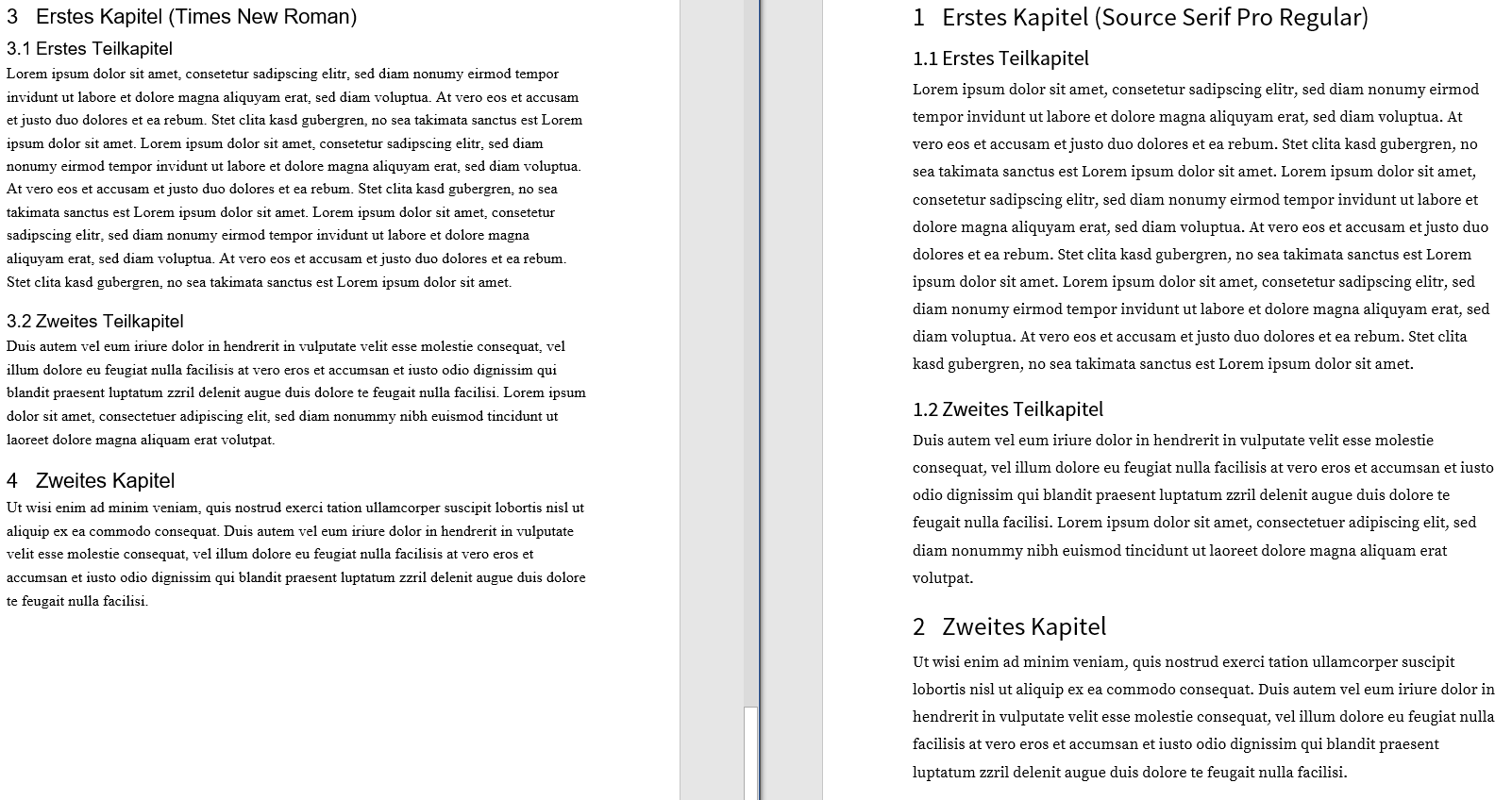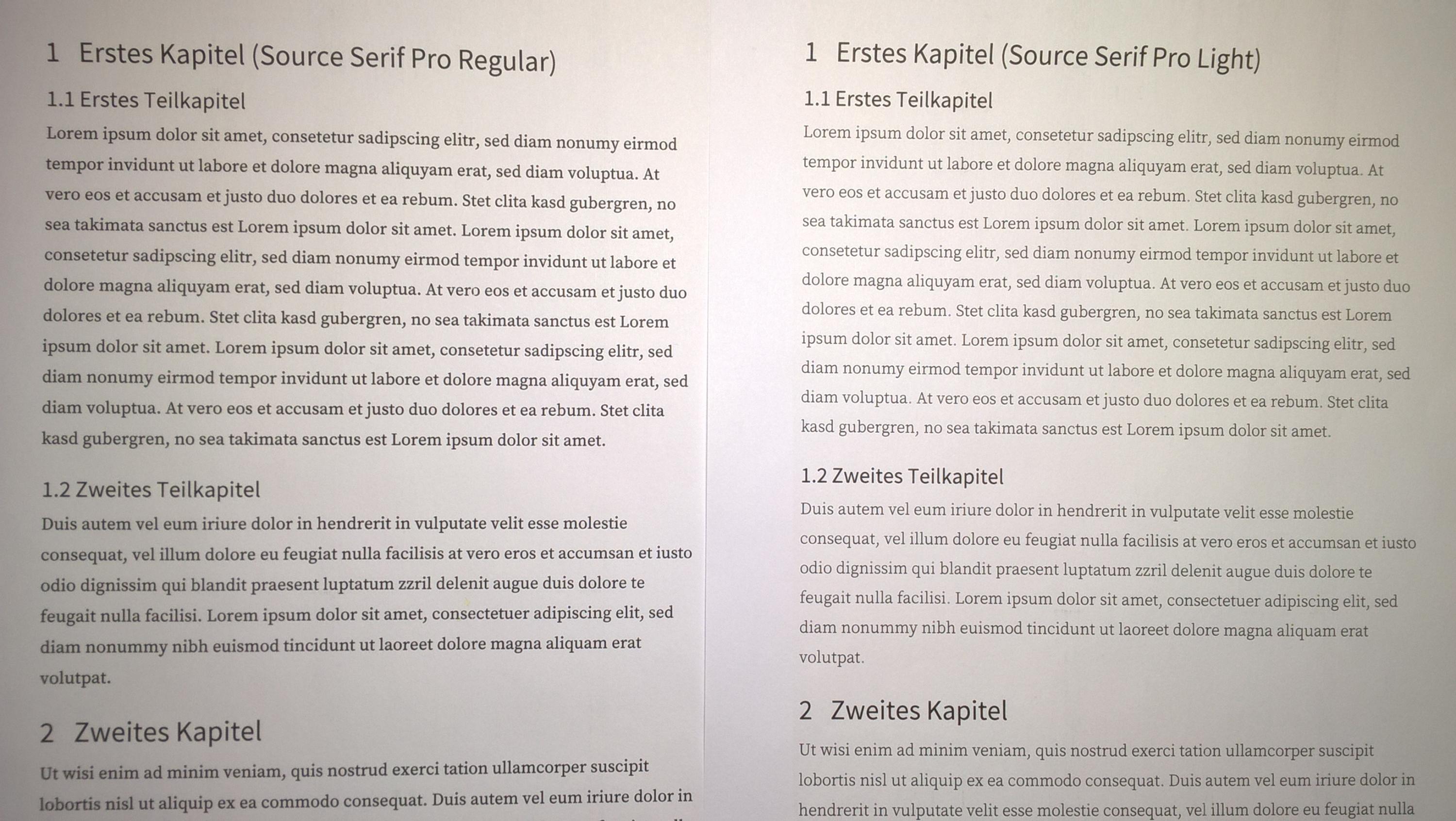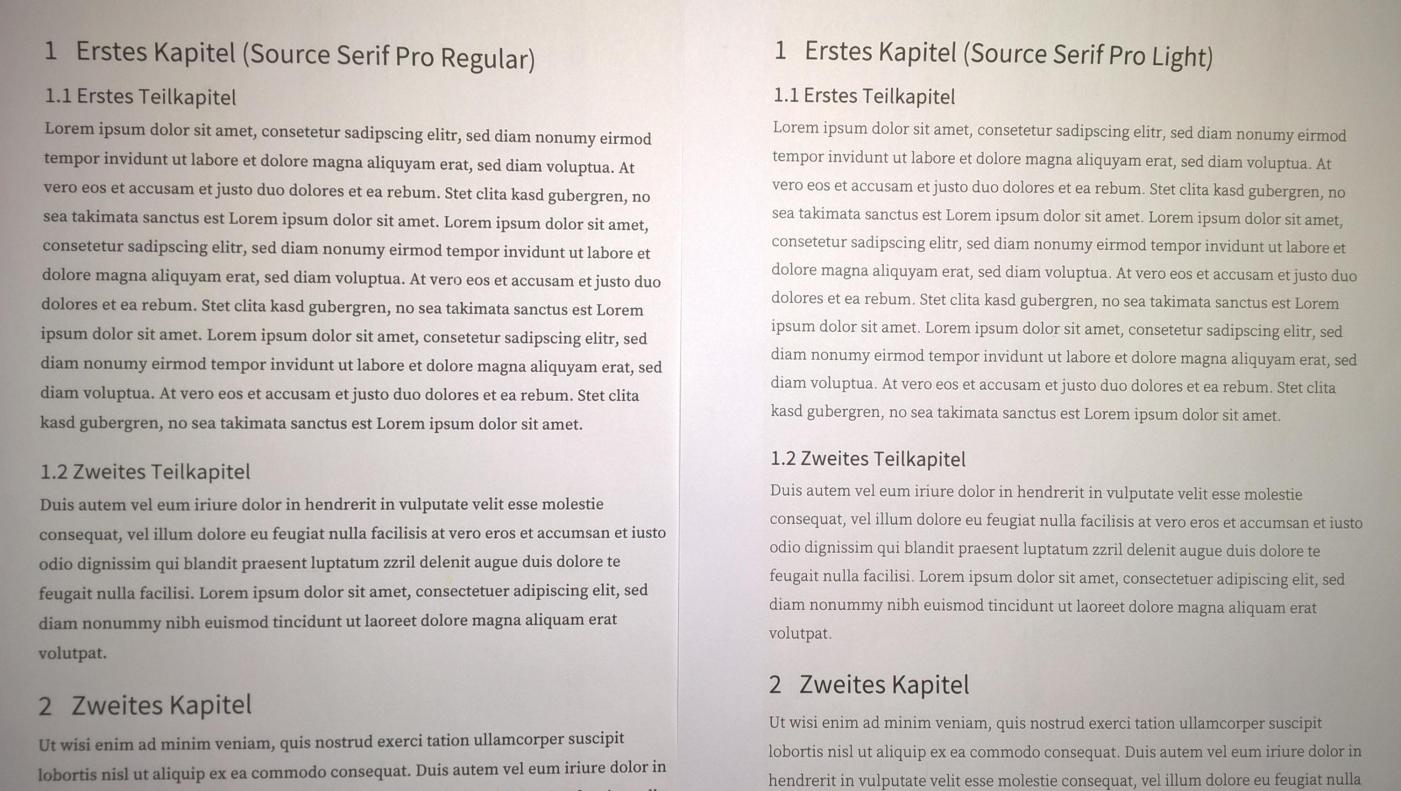
Suche Schriftart für einen Projektbericht
ich muss in der ersten Phase meiner Bachelorarbeit einen Projektbericht anfertigen und suche dafür passende Schriften. Mir persönlich ist die Verwendung von Ligaturen wichtig, da ich finde, dass sie das Schriftbild verbessern.
Ich habe mir bereits einige Schriften von verschiedenen Seiten angeschaut, bin aber nun bei Adobes Source Sans Pro und Source Serif Pro hängengeblieben.
Für Überschriften verwende ich Source Sans Pro mit den von Word (2016) verwendeten Schriftgröße. Der Fließtext hat eine Schriftgröße von 12 pt und nutzt die Schriftart Source Sans Seri Pro Light. (Die Regular-Variante empfand ich zu dick.)
Dazu würde ich gerne eure Meinung hören. Findet ihr das ansprechend, oder habt ihr Tipps oder gar andere Schriftartenvorschläge, die eventuell besser geeignet wären?
PS: Interessanterweise scheint Word 2016 beim Erstellen der PDF-Dateien in Bilder zu konvertieren. In keinem PDF-Programm kann ich den Text markieren. :-?
Das sind gute Schriften, ich denke damit bist du auf der sicheren Seite.
Bei mir am Laserdrucker wirkt der Fließtext aber zu leicht. Finde ihn nicht gut lesbar. Wie wird das später gedruckt? Ein Tintenstrahldrucker dickt den Text noch an, dann ist es vielleicht ok.
danke für deine Antwort. Okay, ich teste es mal hier am Laserdrucker. Ich schreibe das Dokument zurzeit an einem 13"-Notebook, sodass das Schriftbild möglicherweise einfach verfälscht wirkt.
Den Projektbericht werde ich im Copyshop drucken lassen. Die werden vermutlich gute Laserdrucker nutzen.
Schau dir mal auf Druckerchannel die Testberichte an. Es ist keineswegs so, dass das Schriftbild bei teuren und im Ranking höher positionierten Laserdruckern besser ist. Für einen Copyshop dürften Langlebigkeit, Geschwindigkeit, Tonerkosten u. s. w. wichtiger als das Schriftbild sein.
Das wäre sehr ärgerlich. Na gut, dann eventuell doch lieber zuhause drucken? Oder gibt es da bessere Optionen?
Zum Thema: ich habe noch etwas herumprobiert und mir die Variante mit Sans Serif Pro Regular mal ausgedruckt und neben die Light-Variante gelegt. Persönlich finde ich, dass die regular zu aufdringlich wirkt. Ich habe außerdem die Überschriften von den Größen etwas angepasst. Überschrift 1 und Überschrift zwei sind nun jeweils 20 pt und 16 pt groß.
Ich habe auch noch die Source Sans Serif für den Text ausprobiert. Ich denke aber, dass Serifenschriften für Texte im Druck besser geeignet sind. Auch ist der Kontrast höher.
Was meint ihr?
Vor der Entscheidung für einen der Schnitte der Source Sans oder Serif mit einem Probetext in den Copyshop gehen und mit Druckern unterschiedlicher Hersteller ausdrucken lassen, sofern der Copyshop da eine Auswahl hat.
Deine PDF-Dateien sind nicht für den Druck geeignet und ergeben auch auf einem Bürodrucker kein gutes Schriftbild, da alle Schriften gerastert sind.
So, wie die Schrift momentan dargestellt wird, kannst du sie auch nicht gut beurteilen.
Oh, das ist ärgerlich. Kann man Word entsprechend einstellen, dass diese dafür geeignet sind? Ich nahm an, dass die Standardeinstellungen das wohl machen würden, da die Texte aus Word in der Regel ja ausgedruckt werden.
Schau mal in die PDF-Einstellungen von Word 2016: (Datei -> Exportieren -> PDF -> Optionen)
Der Haken bei "Text als Bitmap ..." sollte auf jeden Fall drin sein, vielleicht klappt es ja dann.
Edit 1: Bei mir hat der Export mit den Source Sans/Source Serif Fonts mit Standardeinstellungen problemlos geklappt, d.h. die Fonts sind richtig eingebettet.
Standardeinstellungen von Word 2016 für PDFs:
Edit 2: Vielleicht hast du ja auch den Haken bei "Minimale Größe" gesetzt, dann sind die Einstellungen wieder anders. (Im Umkehrschluss heißt das, dass der Haken bei "Standard" gesetzt sein muss, und nicht bei "minimale Größe") :-D
Nachtrag: Ich habe die Änderungen mal ausprobiert und habe für Source Serif Pro Regular und Light den Fließtext auf 11 pt verkleinert. Selbst so braucht die Schrift noch mehr Platz, als Times New Roman.
Ich habe die PDF mal erzeugt. Auf Seite 7 ist nun mit Times New Roman als Vergleichswert. Mit der Größe sieht die Regular tatsächlich besser aus, finde ich.